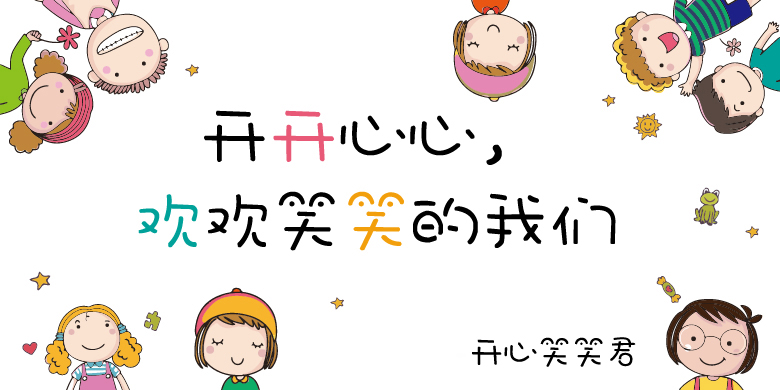
方正字汇-开心笑笑君
方正字汇-开心笑笑君是一款艺术字体,深受广大设计师的喜爱。
字体品牌: 方正字汇 设计师:高宇 字体分类:圆体、创意字体 字体属性:精品字 字符集:大陆简体(GB2312-80) 发布时间: 2018
开心笑笑君线条简单,转折圆滑,重心偏下,部件设计及部件排列透气性很强,给人的感觉是萌萌哒非常可爱。适用于少年儿童类的书刊、品牌广告和产品包装设计,以及社交网络的个性化用字。